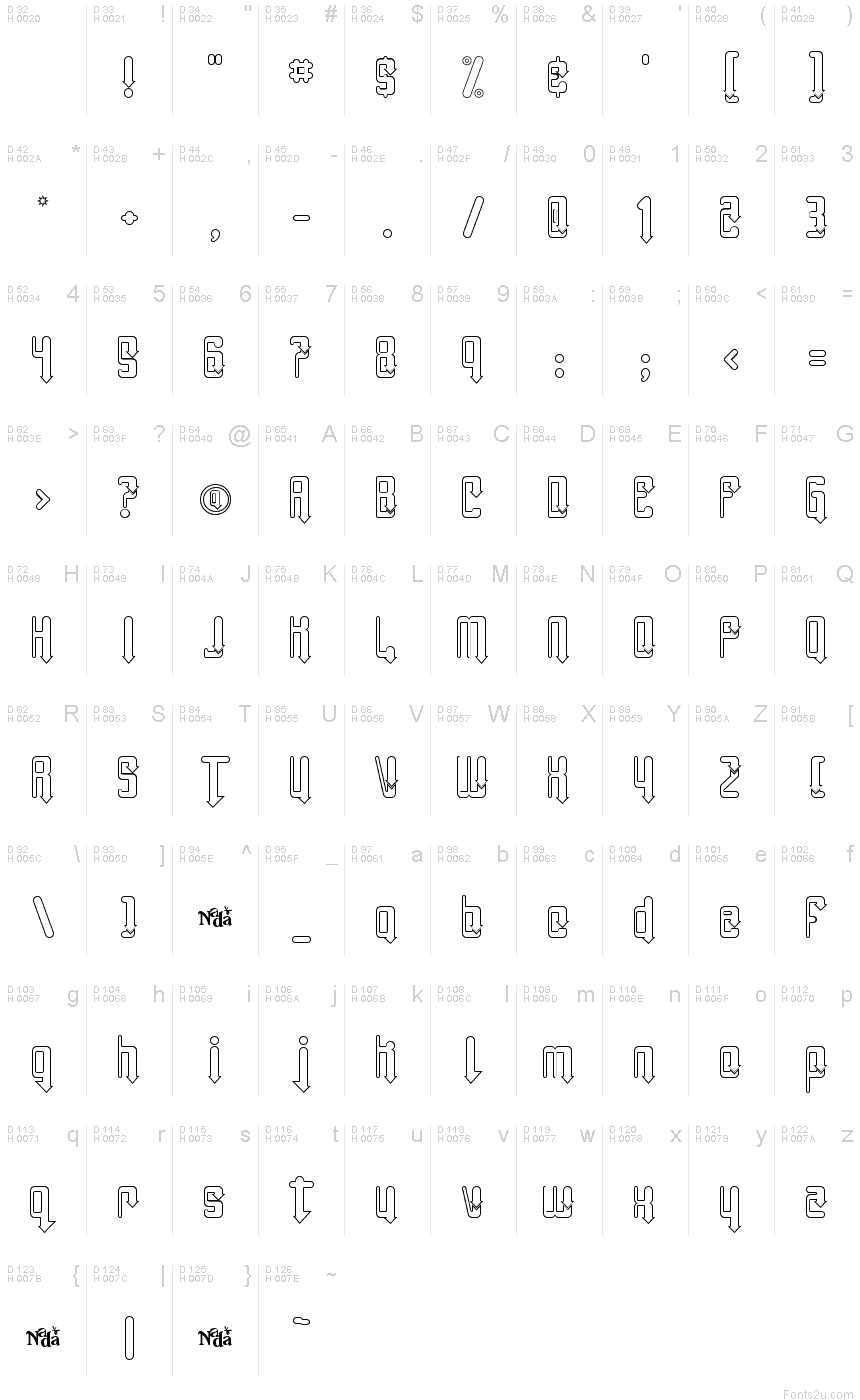
Angie TanLines di R.Gast - GreyWolf WebWorks è un font display gratuito della famiglia Angie, composto da tratti tubolari fluidi che terminano in punte di freccia marcate. Ogni lettera ricorda un tubo al neon piegato o il contorno di un palloncino, conferendo alle parole un senso di movimento e direzione anche quando sono statiche. L'interno aperto e arioso conferisce un aspetto leggero e giocoso, mentre lo spessore costante del tratto assicura nitidezza e leggibilità nelle dimensioni più grandi.
Questo font gratuito, Angie TanLines, brilla su poster per bambini, grafiche per eventi estivi, loghi divertenti, titoli di giochi, inviti a feste e grafiche per social media che necessitano di un chiaro "punto" visivo. Le forme delle lettere a freccia guidano naturalmente l'occhio lungo i titoli e le frasi brevi, quindi funziona al meglio come intestazione audace abbinata a un semplice font sans serif per il corpo del testo. Provatelo in grande, con molto spazio attorno, per far risaltare davvero le frecce delineate e gli angoli arrotondati.